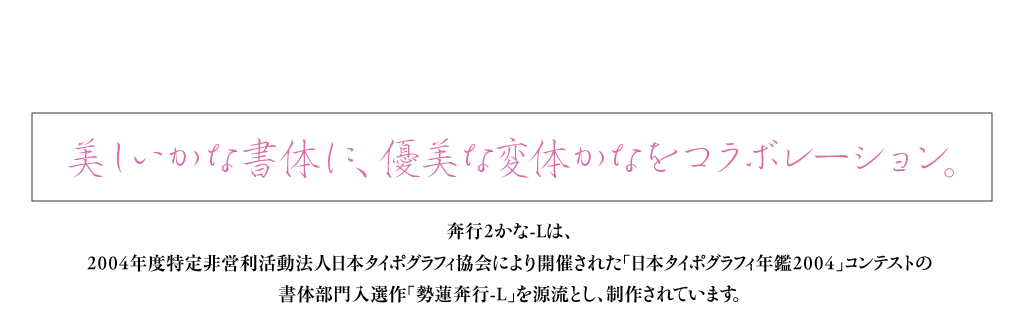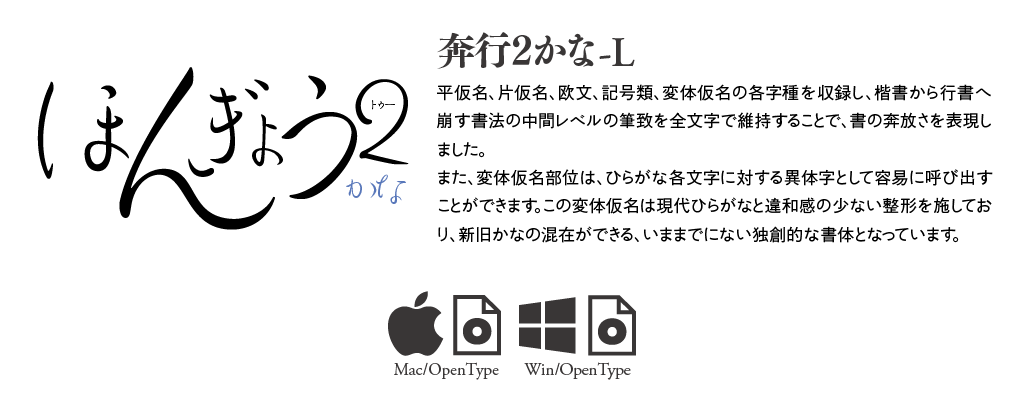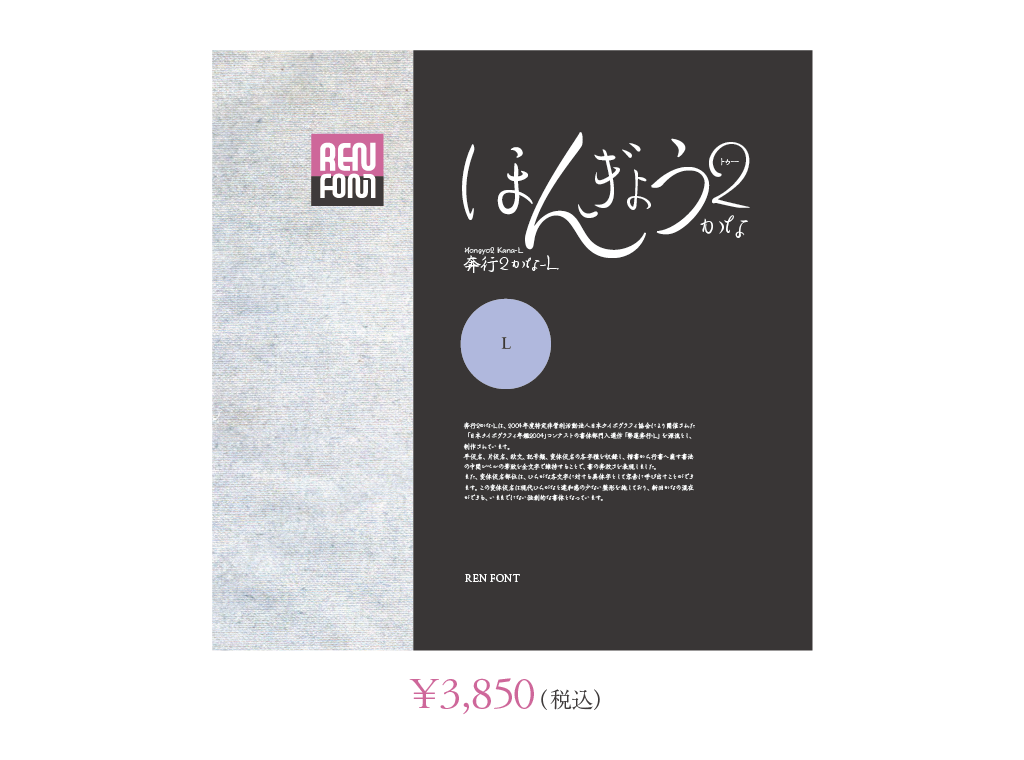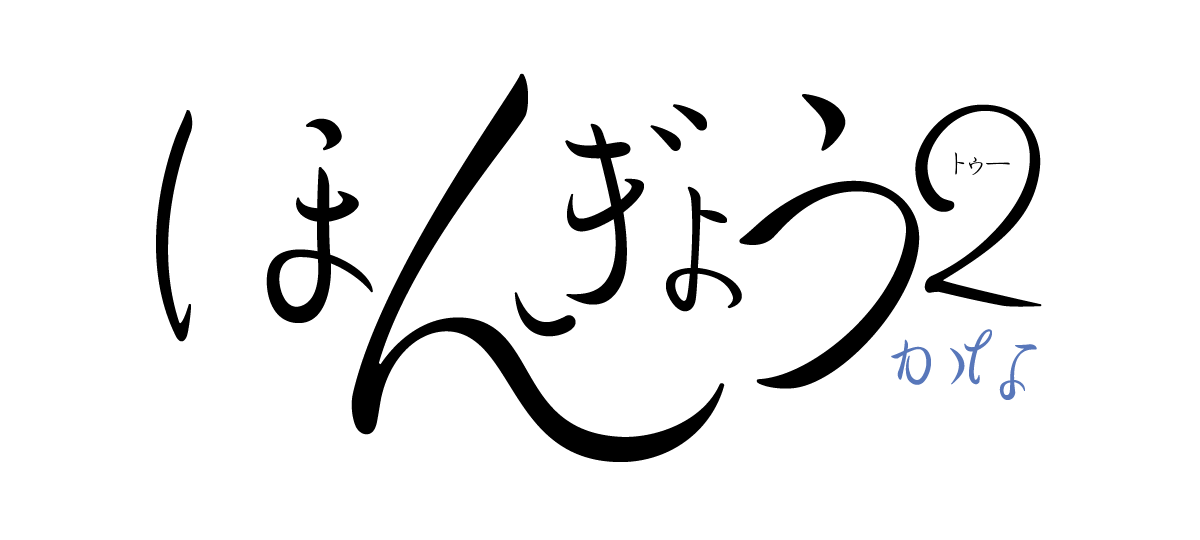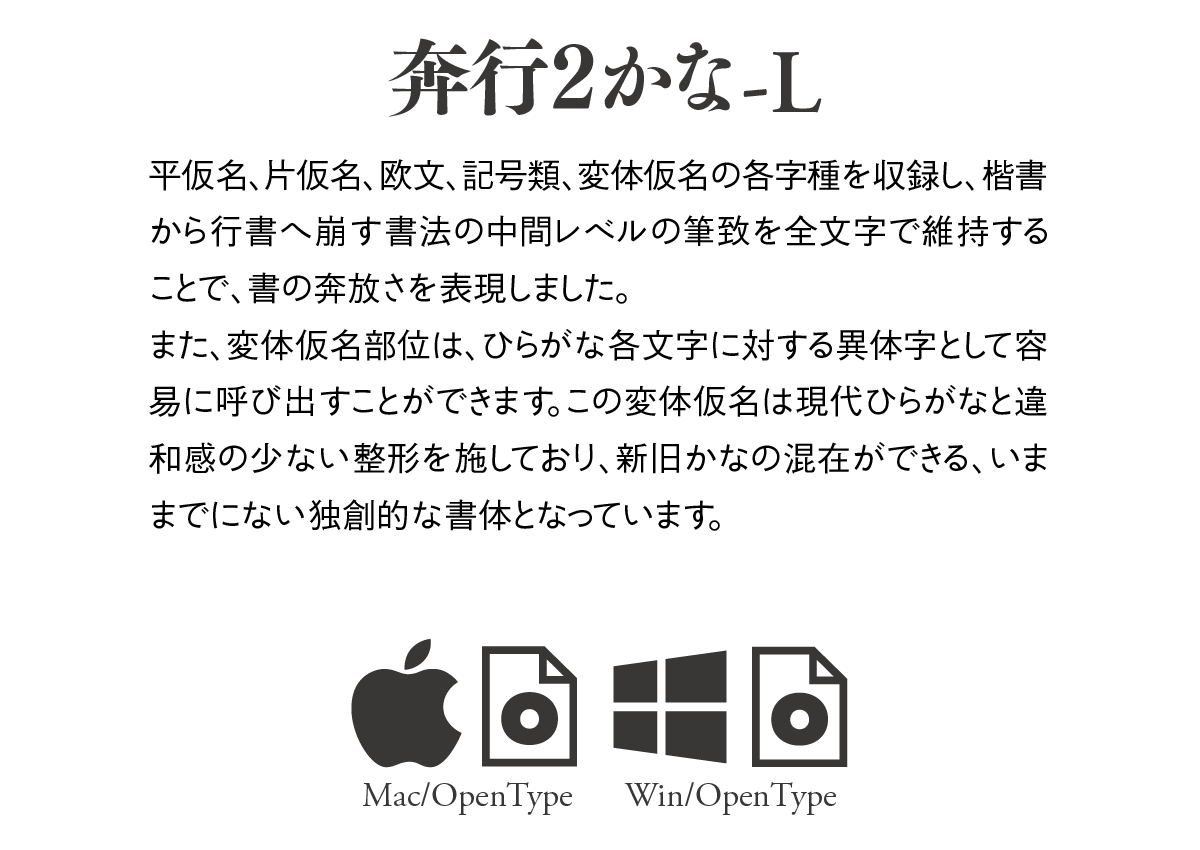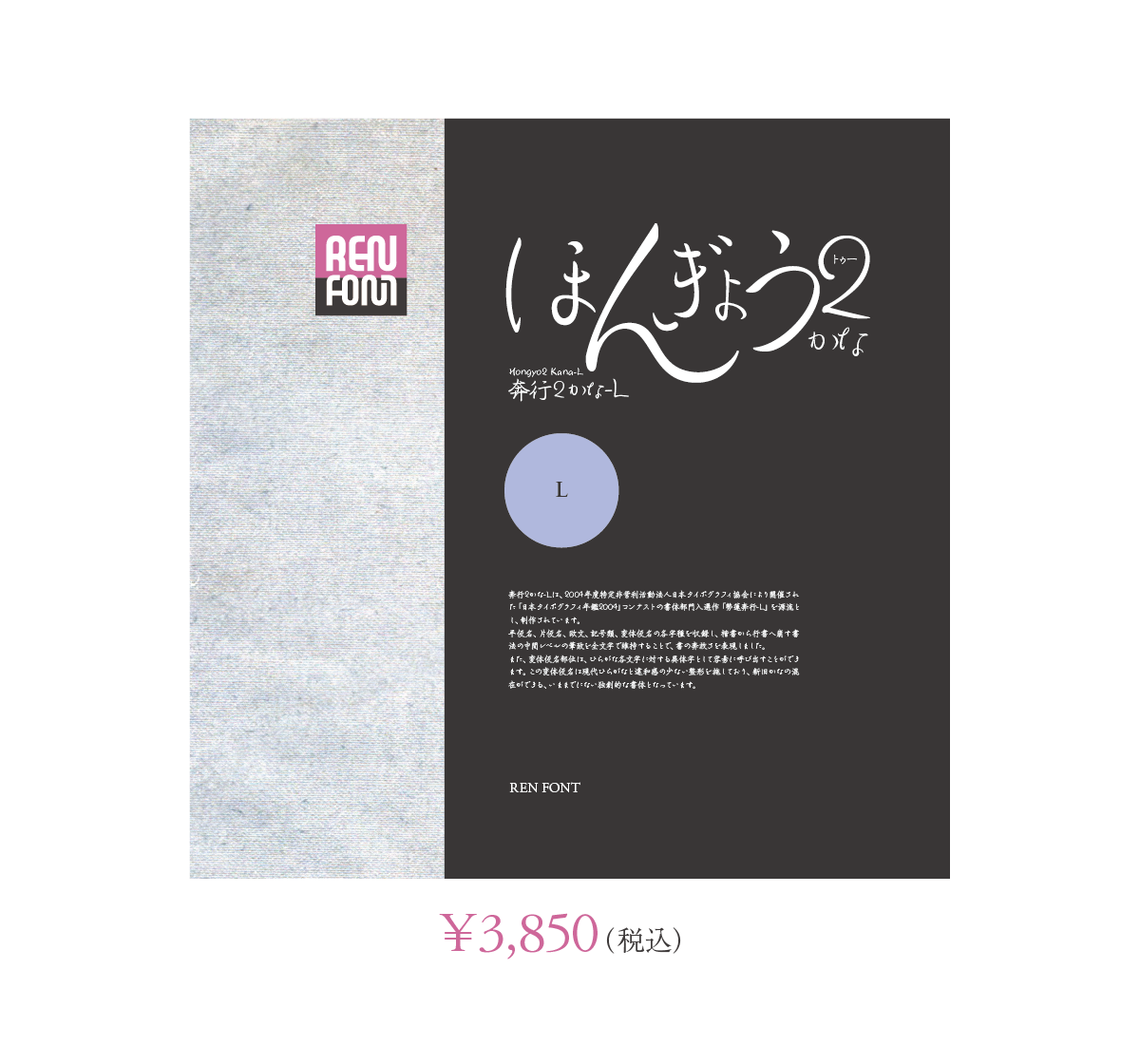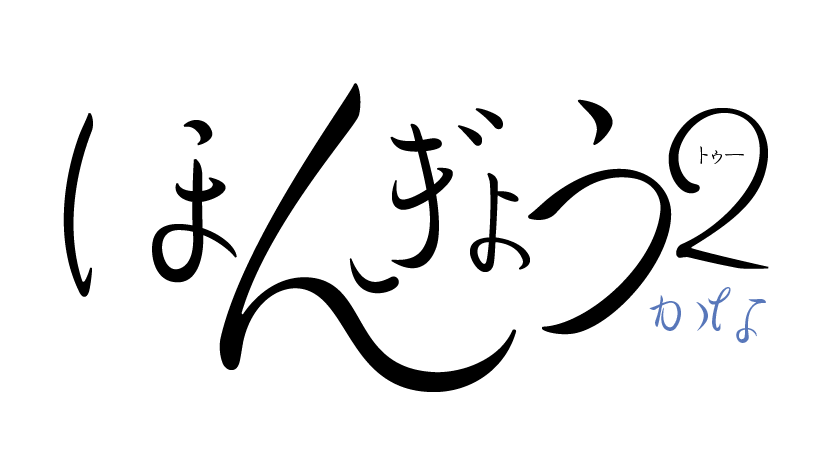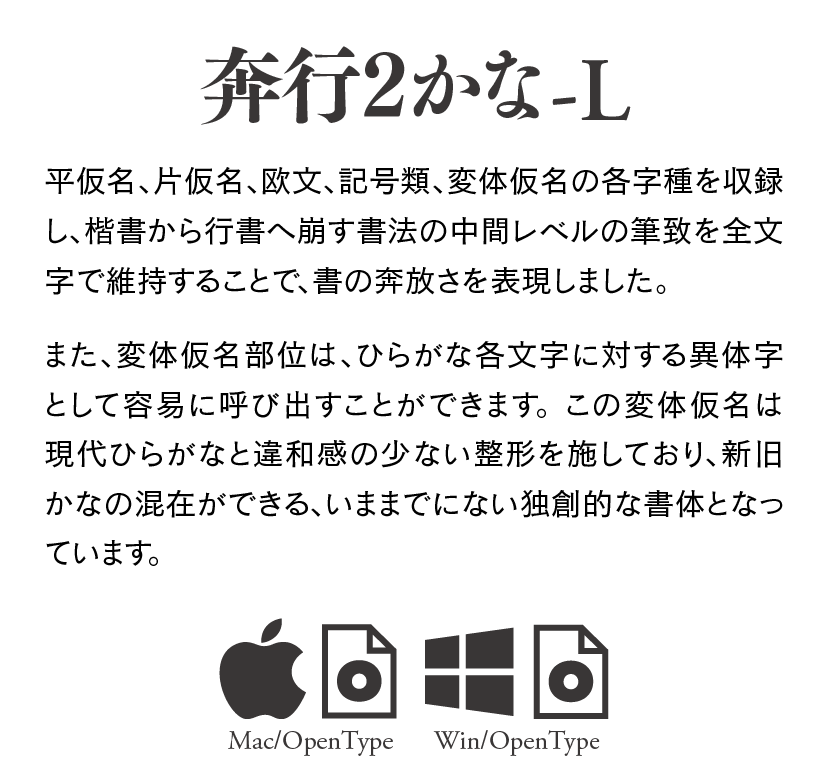
優美な仮名文字、変体仮名も収録した 奔行2かな-L Single Weight Font
収録文字
1091文字
内訳
この書体は、現代かな部分を Adobe Japan 1.0文字セットに準拠し、変体仮名部位を独自のコードに配置しております。含まれる文字種は以下の通りです。
仮名
・平仮名(全角・半角全文字)・片仮名(全角・半角全文字)
・変体仮名(全角のみ、320文字)
欧文
・プロポーショナル欧文 94文字
・全角欧文 94文字
記号類
・常用する句読点類・約物類のみ
罫線類
・罫線素片類(全角・半角)